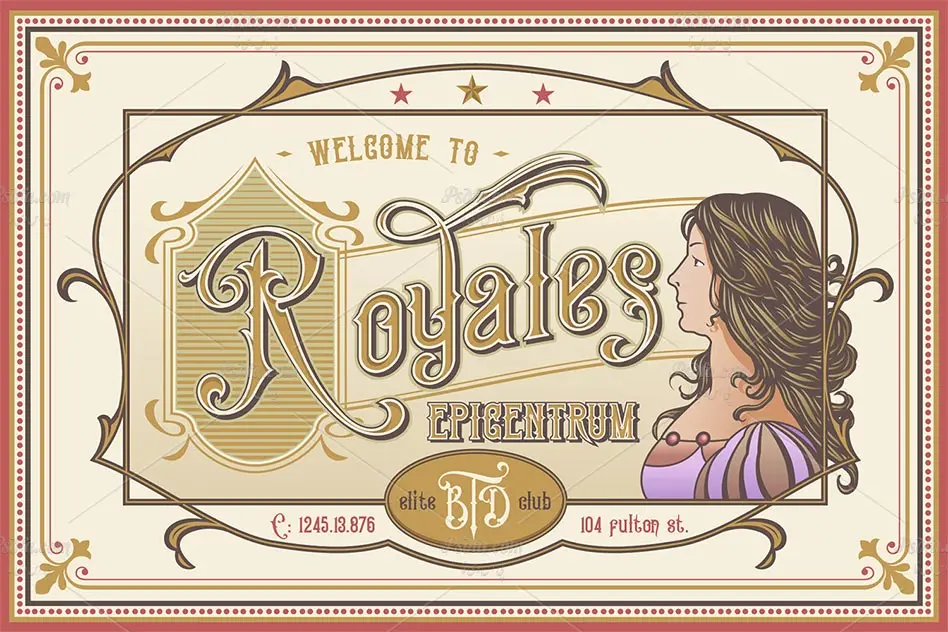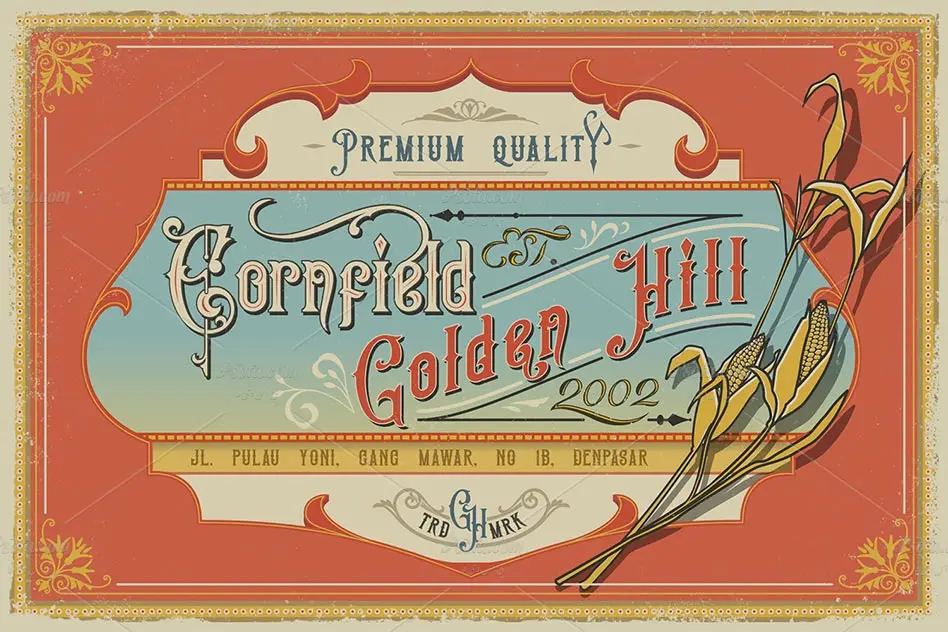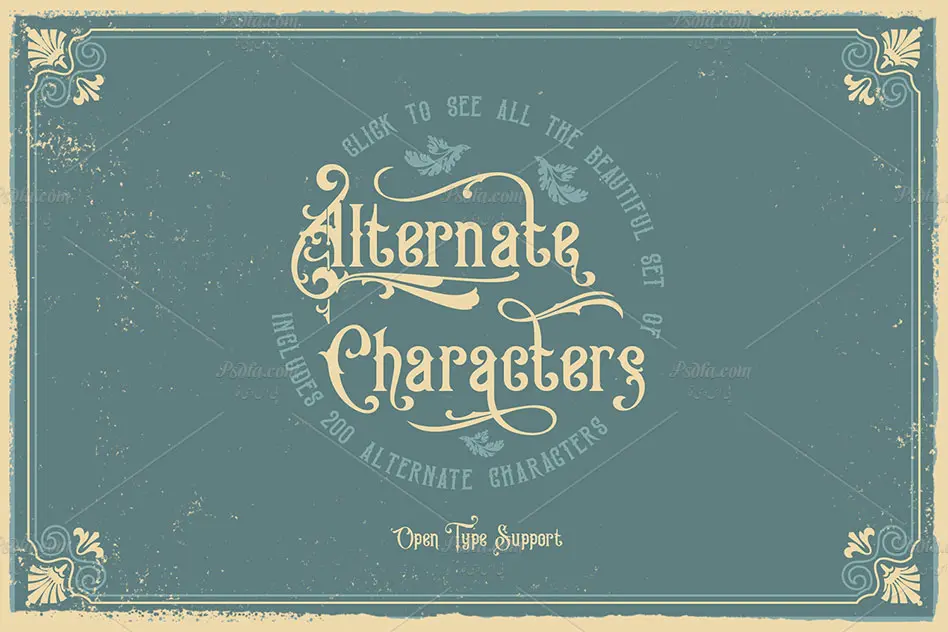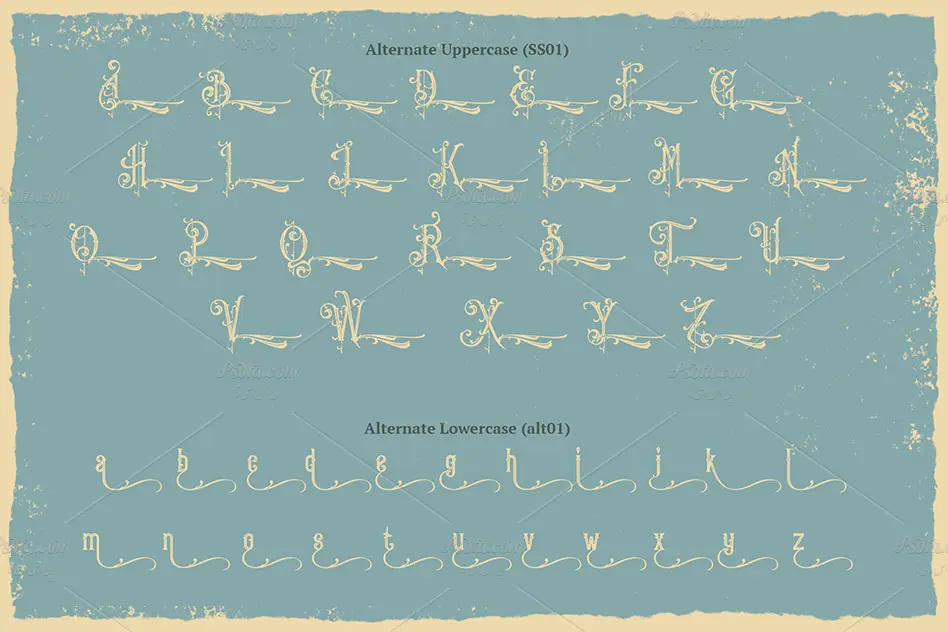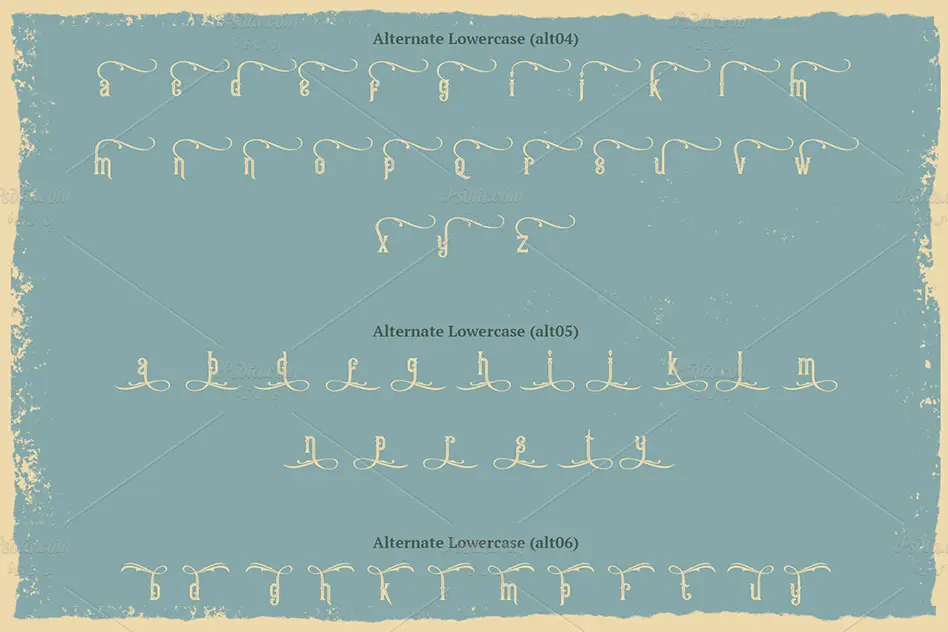
فونت انگلیسی قدیمی ویکتوریایی مناسب برای طراحی
فونت انگلیسی قدیمی ویکتوریایی
در این مطلب شاهد مجموعه فونت انگلیسی قدیمی ویکتوریایی Queen Victoria و King Edward مناسب جهت استفاده در طراحی و گرافیک می باشید. این مجموعه فونت که از خانواده فونت های ویکتوریا می باشد از دسته فونت های قدیمی و وینتج است که با فرمت های ttf و otf در سایت قرار داده شده اند. شما می توانید با نصب این مجموعه فونت در پوشه فونت های سیستم خود از آن ها به طور مستقیم در تمام نرم افزار گرافیکی و ویراشگر متن از جمله نرم افزار فتوشاپ ، مجموعه نرم افزار آفیس و … استفاده کنید. از این مجموعه فونت می توان در ایجاد پوسترهایی با طرح های قدیمی و وینتج استفاده نمود.
- به همراه وکتور عناصر تزئینی گل و حاشیه